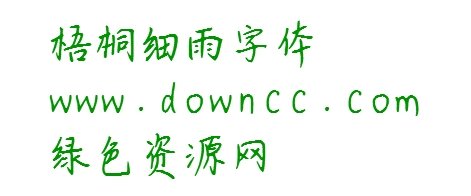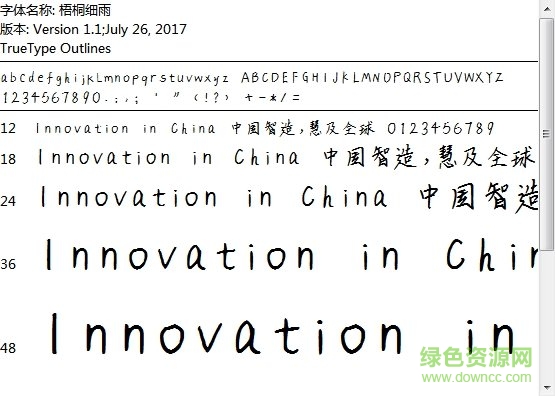
梧桐細(xì)雨體ttf是一款用筆溫柔而不失力度的手寫字體,干凈優(yōu)雅的筆觸、筆畫清晰而有力,給人清新淡泊的視覺(jué)美感,綠色資源網(wǎng)歡迎大家免費(fèi)下載!
本字庫(kù)是在國(guó)家標(biāo)準(zhǔn)簡(jiǎn)體字庫(kù)GB2312所包含6763漢字的基礎(chǔ)上,又增加了近200常用字,已經(jīng)覆蓋了大陸99.75%的漢字使用頻率,足以滿足日常需求。